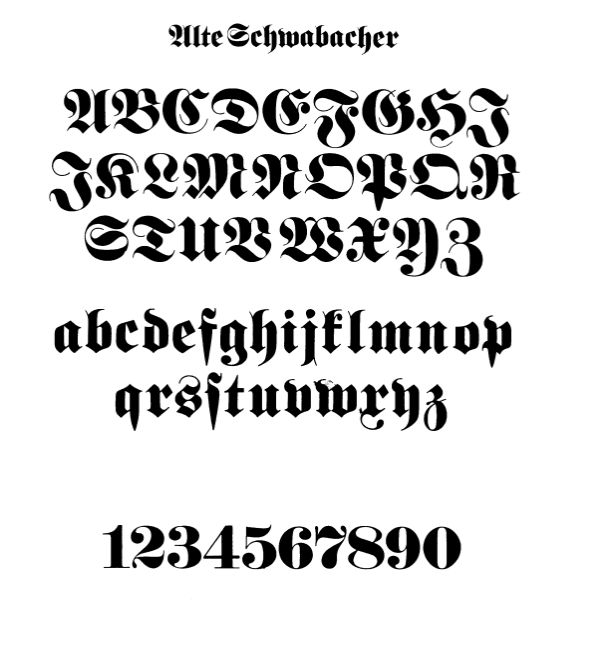
Шрифт Gothic 1 , Готические — Прочие шрифты
Franklin Gothic и связанные с ним начертания — это большое семейство шрифтов без засечек в индустриальном или гротескном стиле, разработанных в начале 20-го века шрифтовой литейной American Type Founders (ATF) и приписываемых ее главному дизайнеру Моррису Фуллеру Бентону .
Franklin Gothic использовался во многих рекламных объявлениях и заголовках газет. Шрифт продолжает оставаться на виду, появляясь в самых разных средствах массовой информации, от книг до рекламных щитов. Несмотря на период затмения в 1930-х годах, после появления европейских лиц, таких как Kabel и Futura , они были заново открыты американскими дизайнерами в 1940-х годах и с тех пор остаются популярными. Семейство Benton’s Franklin Gothic — это набор прочных дизайнов, особенно подходящих для демонстрации и коммерческого использования, например заголовков, а не расширенного текста. С тех пор было сделано много версий и приспособлений.
Вероятно, самым известным расширением Franklin Gothic является ITC Franklin Gothic 1970-х Виктора Карузо, которое расширяет серию, чтобы включить в нее книжные веса, похожие на News Gothic Бентона, в стиле 1970 — х годов с высокой высотой x . Частично он входит в состав Microsoft Windows .
История
Руководство, объясняющее названия, используемые ATF для их многих несколько связанных «готических» типов.Franklin Gothic
- Франклин Готик (1902)
- Франклин готический сжатый + дополнительный сжатый
(1906) - Франклин Готический курсив (1910)
- Франклин готический конденсированный затененный (1912)
Спустя много лет литейный завод снова расширил линейку, добавив еще два варианта:
- Franklin Gothic Wide (1952), разработанный Джоном Л.
«Бадом» Реншоу. - Франклин готический сжатый курсив (1967) разработан Уидоном Дэвисом
Его можно отличить от других шрифтов без засечек по его более традиционному двухуровневому a и особенно g (двухуровневый g s, распространенный в шрифтах с засечками, редко встречается в шрифтах без засечек, следующих немецким моделям, но был довольно распространен в Америке и США). Британский дизайн того периода), хвост
Копии горячего металла
Barnhart Brothers & Spindler скопировали лицо как Gothic # 1 , в то время как Linotype и Intertype назвали свои копии Gothic # 16 . Копия Monotype сохранила название Franklin Gothic , но из-за требований к механической композиции их версия была изменена, чтобы соответствовать стандартной аранжировке. Версия Ludlow была известна как Square Gothic Heavy.
Копии холодного типа
Из-за послевоенной популярности готических лиц большинство производителей холодного шрифта предлагали свои собственные версии
Цифровые копии
Цифровые копии были сделаны Adobe , International Typeface Corporation , Monotype Imaging и URW . Виктор Карузо нарисовал мультимедийное семейство для International Typeface Corporation (ITC) в 1979 году, а в 1991 году ITC заказал Font Bureau в Бостоне для создания сжатых, сжатых и дополнительных сжатых версий ITC Franklin Gothic. Версия Bitstream называется Gothic 744. Microsoft Windows распространяла «Franklin Gothic Medium», один из вариантов шрифта ITC, во всех копиях, начиная с Windows 95 .
Хотя ITC Franklin Gothic является наиболее распространенным выпуском, его критиковали за значительное изменение структуры семейства. Каллиграф и историк дизайна Пол Шоу утверждал, что это была неудача для «возиться с характерным Franklin Gothic g. В ITC Franklin Gothic … ухо на g продолжает выскакивать, как школьник, чрезмерно жаждущий ответить на вопрос».
Открытая интерпретация Franklin Gothic была сделана Impallari Type как Libre Franklin. Libre Franklin доступен в Google Fonts .
Альтернативная готика
Альтернативная готика была разработана М.Ф. Бентоном для ATF в 1903 году. По сути, это умеренно жирная сокращенная версия Franklin Gothic, выполненная в трех пронумерованных ширинах. № 1 является наиболее сжатым, 3 — наименее.
Копии горячего металла
Это лицо было скопировано Monotype под тем же именем, # 1 Ludlow , Linotype и Intertype, что и Gothic Condensed. Ludlow’s Trade Gothic Condensed также очень похож. Было сделано два варианта:
- Альтернативная модернизированная готика (1927, монотипия ), добавлены тринадцать альтернативных персонажей, нарисованных Солом Хессом .
- Краткий готический план (1953, Ладлоу ), по сути, является наброском Альтернативной готики №2.
Копии холодного типа
Альтернативная готика была скопирована Compugraphic как альпийская готика.